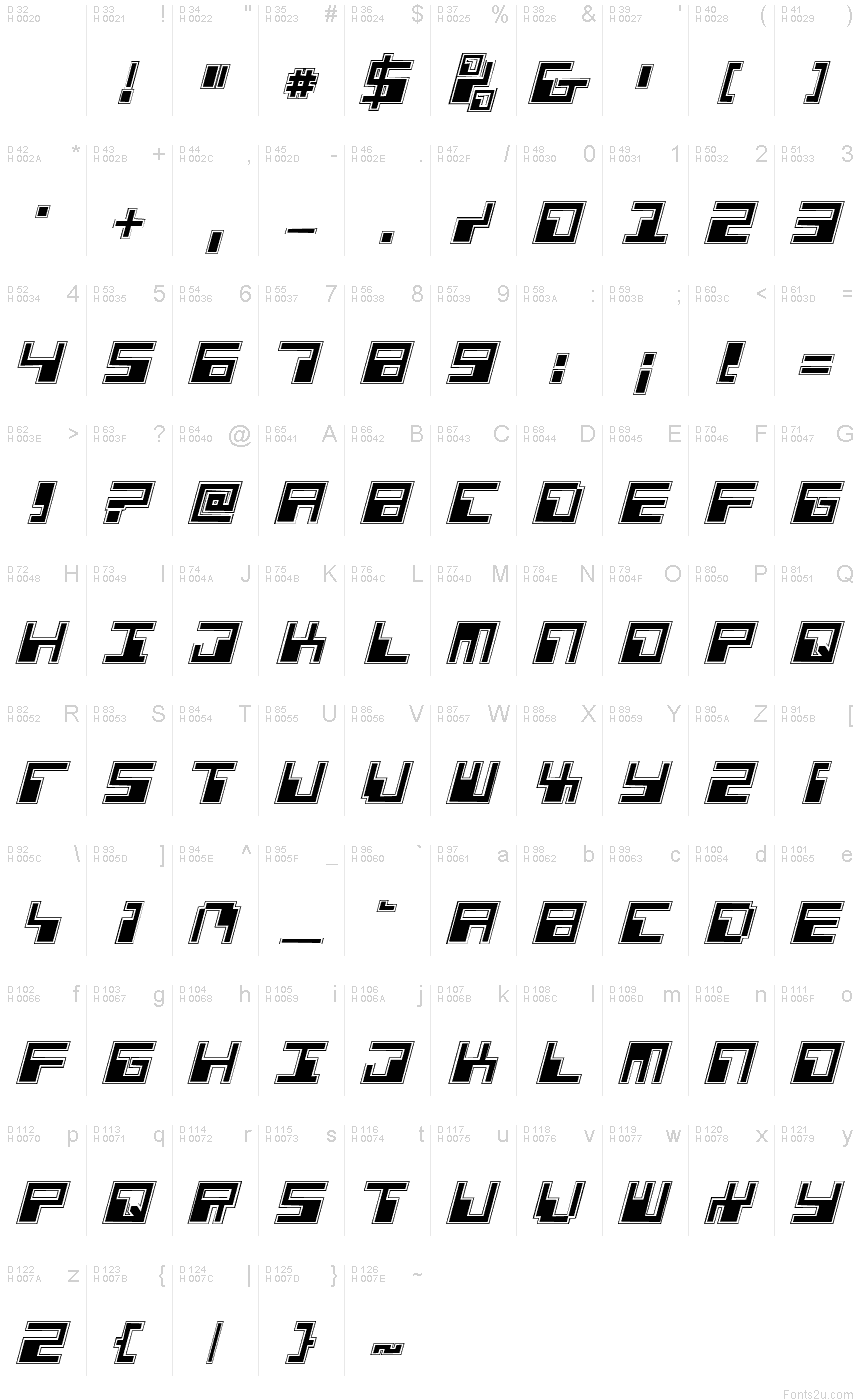
Phaser Bank Pro Italic, autorstwa Iconian Fonts, to darmowy, futurystyczny font w stylu techno, zbudowany z szerokich, pochylonych do przodu liter z wyraźnymi liniami wewnętrznymi. Kwadratowe krzywe, ścięte rogi i warstwowe obrysy nadają krojowi charakter oznaczeń na statkach kosmicznych lub panelu kontrolnym automatu do gier.
Ten darmowy font świetnie sprawdzi się na plakatach science-fiction, w brandingu e-sportowym, logotypach gier, na okładkach albumów, planszach tytułowych i w krótkich nagłówkach. Szerokie kształty i powtarzająca się wewnętrzna linia potrafią utrzymać kompozycję bez zbędnych ozdobników, szczególnie w przypadku krótkich tekstów.